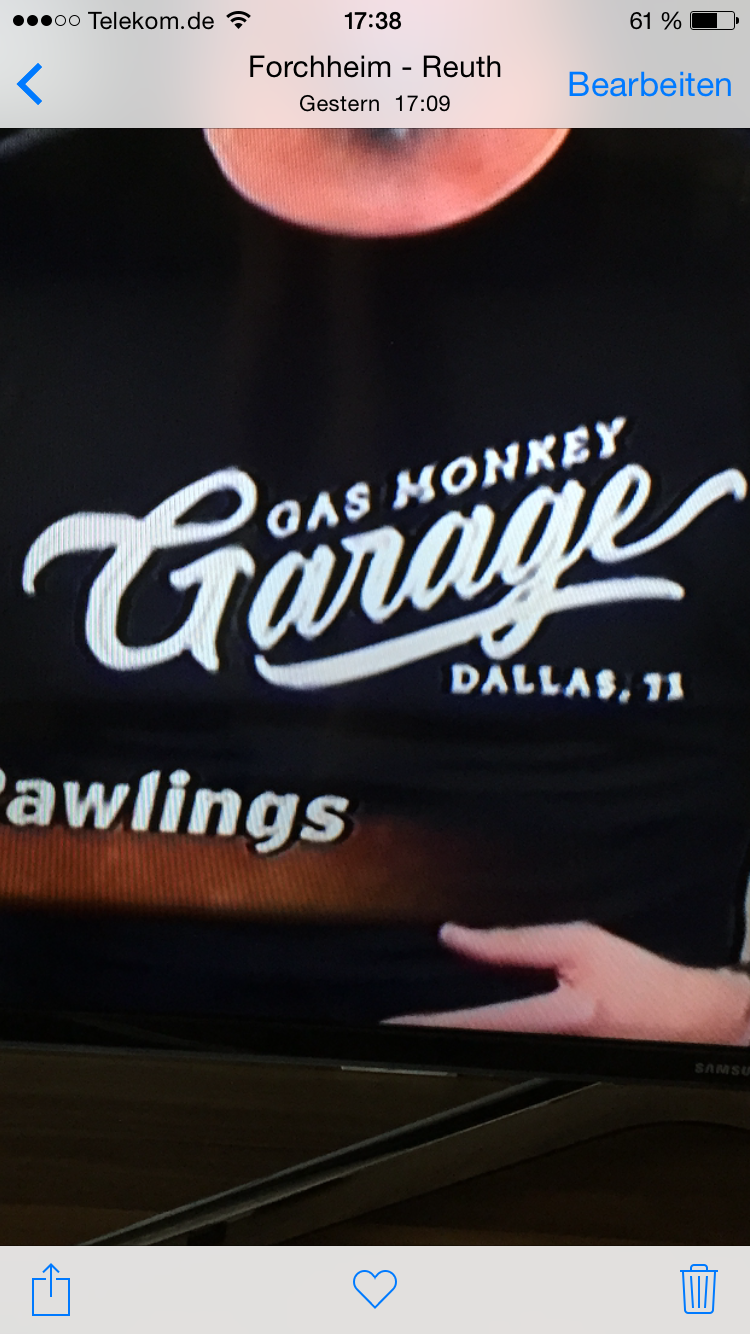
Hi, ich würde mir gerne die Schriftart mit der das Wort Garage geschrieben ist auf den PC laden, finde aber nirgends wie die heißt.
Hi, solche Schriften findet man unter „Script“!